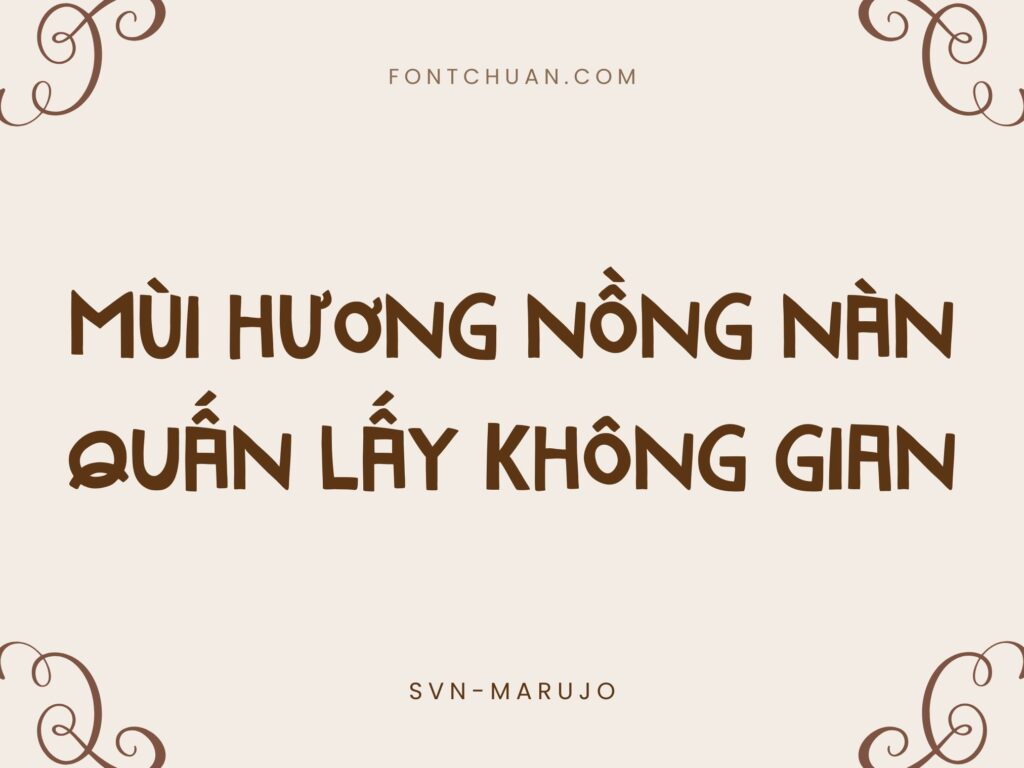
Font SVN Marujo Việt Hóa
Font SVN Marujo là phiên bản Việt hóa của kiểu chữ Marujo, được thực hiện bởi STYLEno.1 Fonts. Marujo là một kiểu chữ trang trí độc đáo, lấy cảm hứng từ các tác phẩm nghệ thuật có liên quan đến hàng hải, đặc biệt từ nghệ sĩ người Brazil Arthur Bispo do Rosário. Font được phát triển với nhiều phong cách khác nhau như Regular, Light, phiên bản sọc, phiên bản chấm và bóng đổ, cùng một font hình ảnh chuyên đề hàng hải. Với cấu trúc phá cách và tính nghệ thuật cao, Marujo mang đến trải nghiệm thị giác đầy ấn tượng và cá tính. Font hỗ trợ đa ngôn ngữ, bao gồm các ký tự chữ hoa, chữ thường, số và dấu câu.
SVN Marujo phù hợp cho các thiết kế như poster chủ đề, bìa sách, tiêu đề sự kiện hoặc các ấn phẩm truyền thông sáng tạo. Các ngành nghề như quảng cáo, giáo dục và công nghệ có thể ứng dụng hiệu quả font này trong những thiết kế cần tạo điểm nhấn sáng tạo. Ngoài ra, font cũng đặc biệt phù hợp với các sự kiện như Tết, Giáng sinh, Halloween và các lễ hội khác.